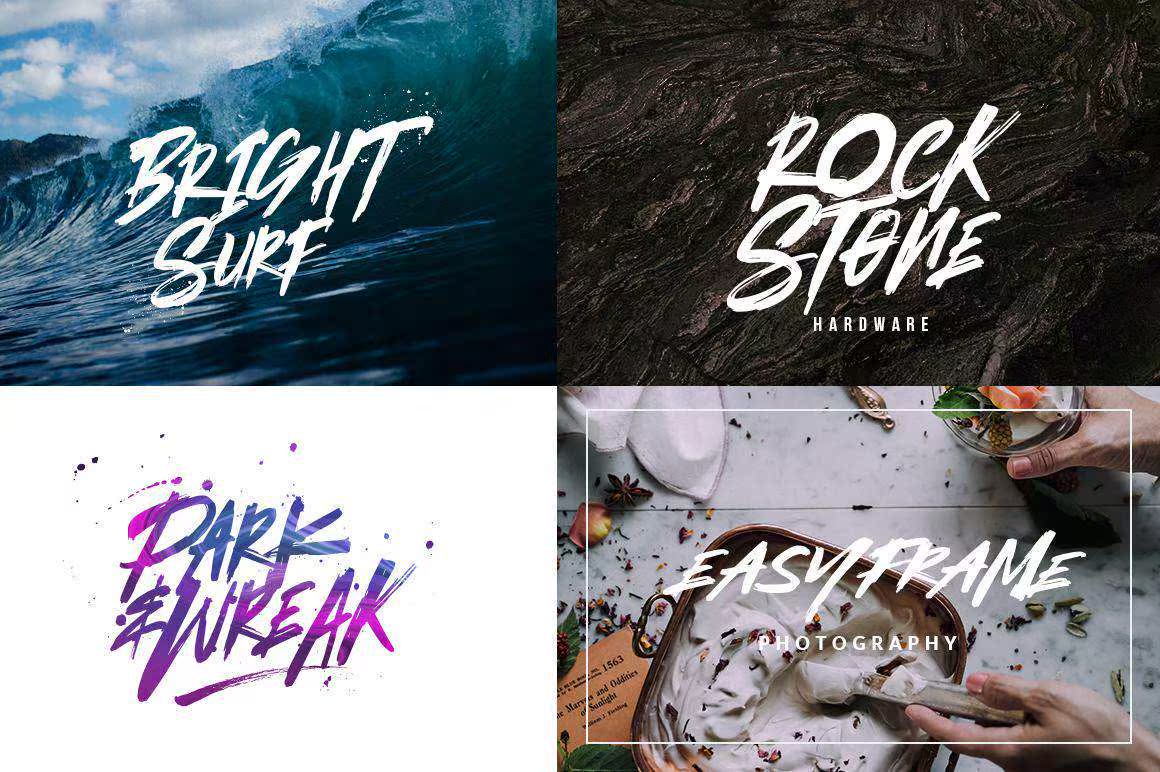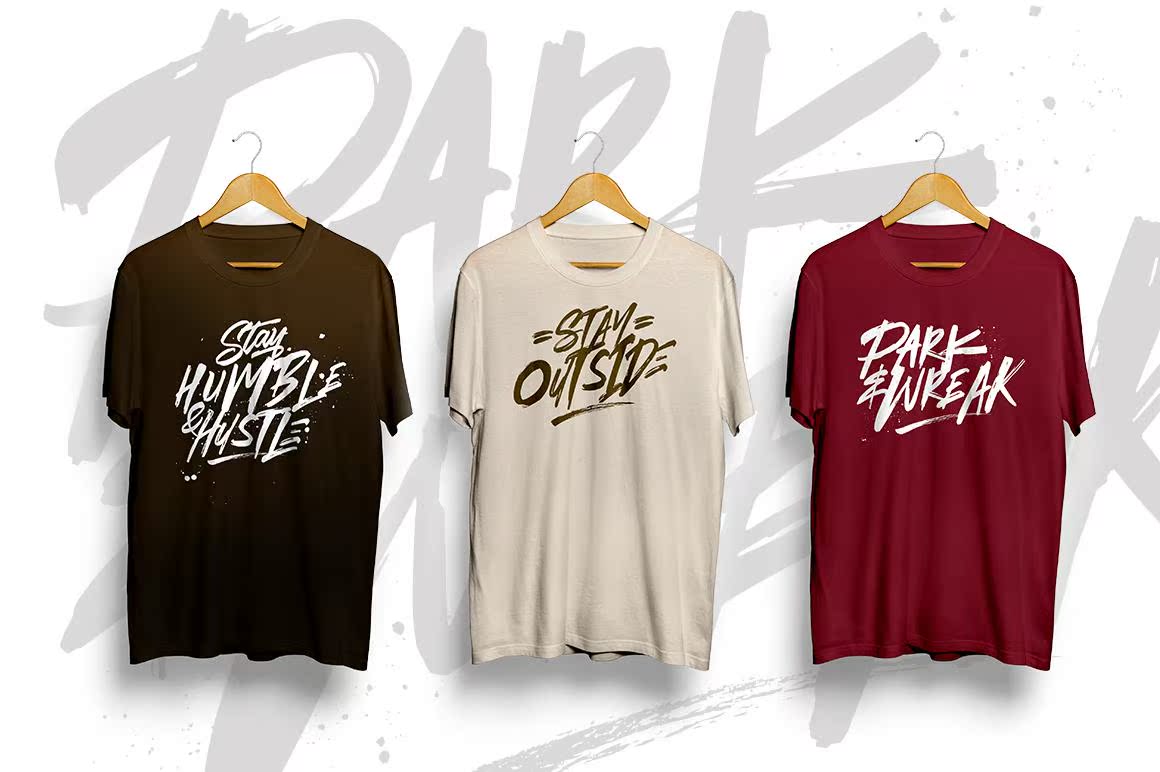
Ember Blazeish and MadeFontBrush结合了生活方式和街头风格的笔刷字体。通过特别注意快速笔划和清晰细节,Ember Blazeish能够快速准确地传递信息,无论是对徽标、服装、报价、产品包装还是任何需要使用Urbo-boost的内容都是理想的。Ember Blazeish and MadeFontBrush,结合生活方式和街头智慧画笔字体。特别注意快速笔触和清晰细节,Ember Blaze可以快速、准确地传递信息,包括理想的日志、服装、报价、产品包装或任何需要通过图形加以提升的内容。